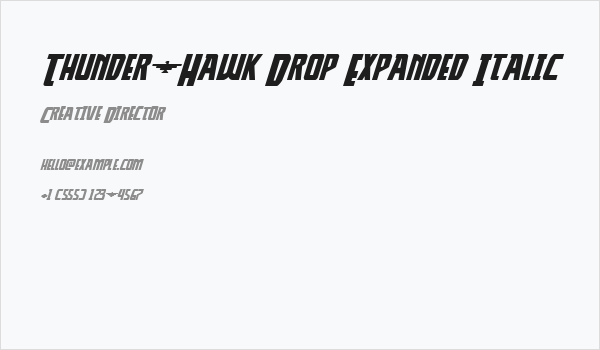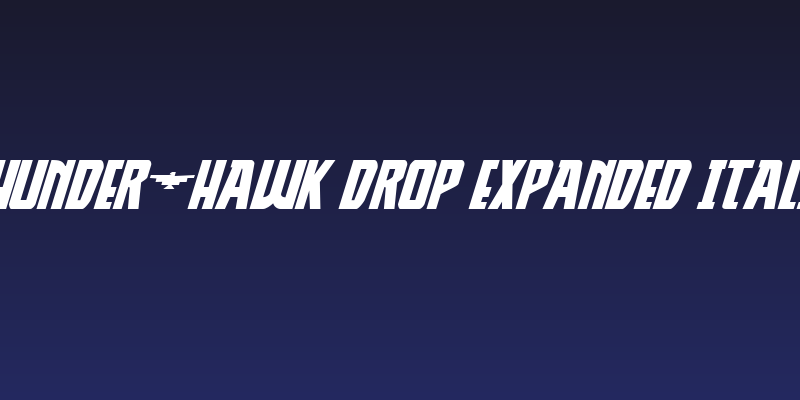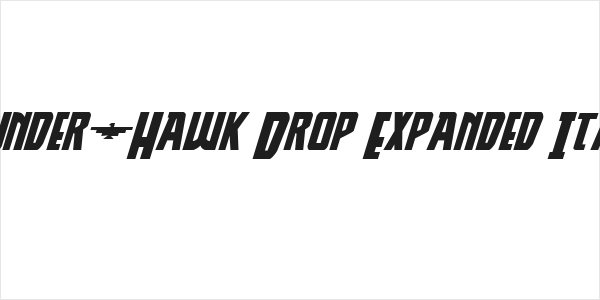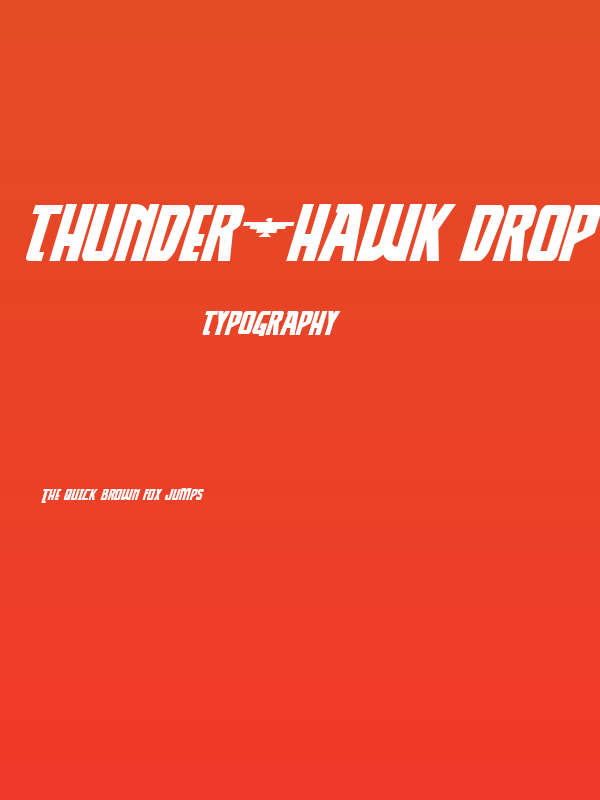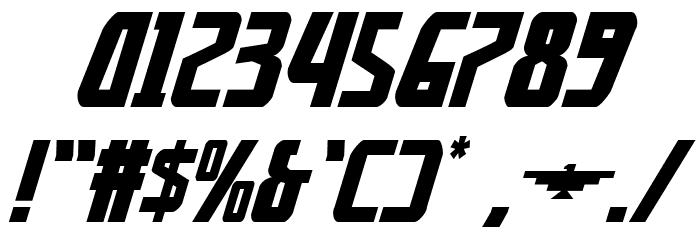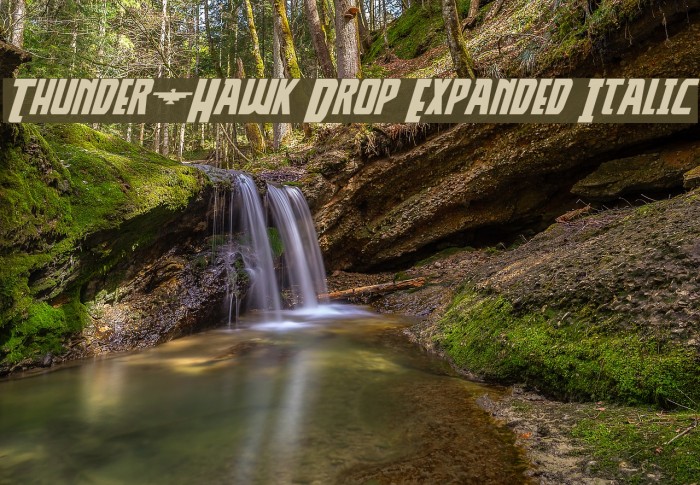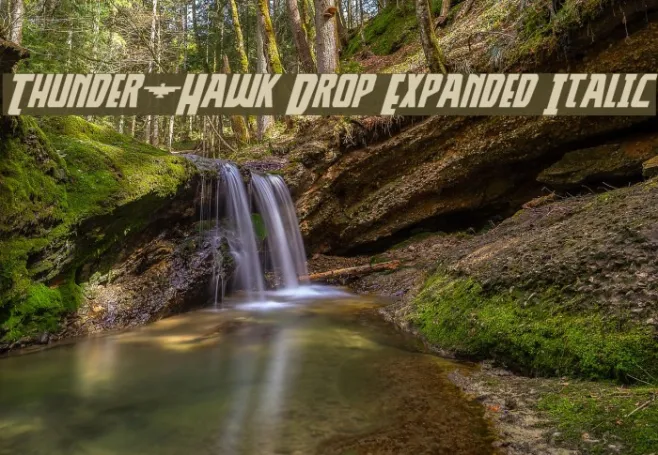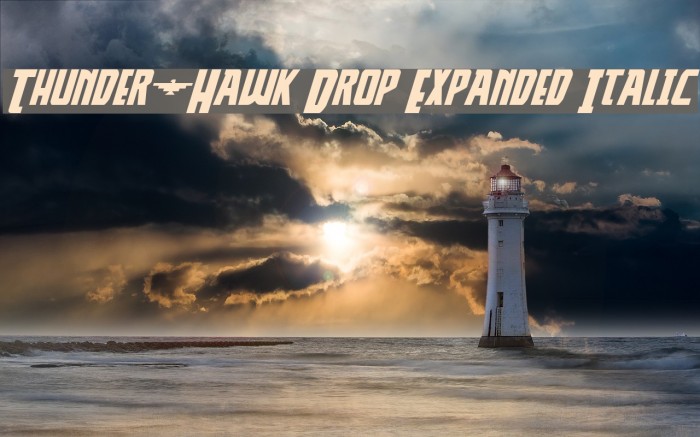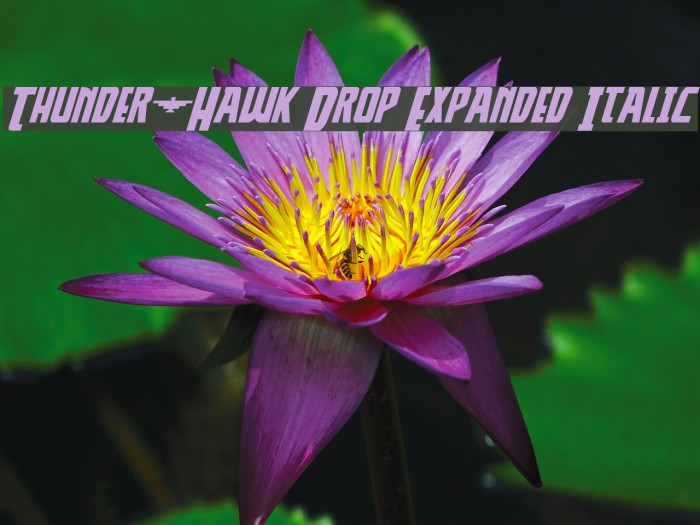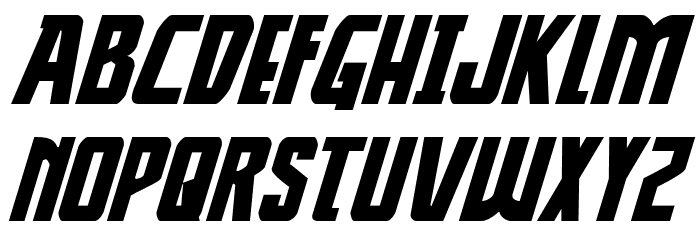
Thunder-Hawk Drop Expanded Italic Font
| Projets proposés | Ideal for sports branding, action-themed posters, video game titles, and dynamic advertising campaigns. |